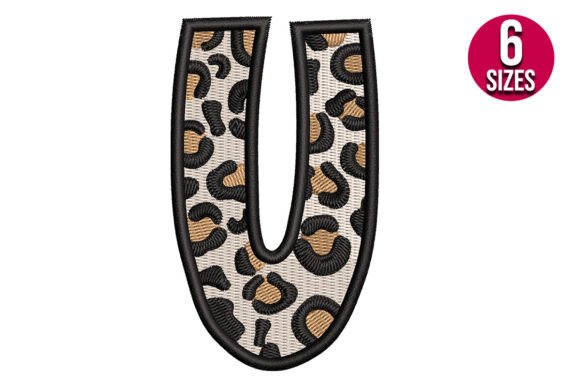
Leopard Print Alphabet Font Letter U
Urbano, ousado e felino: Review da Fonte de Letra U em Estampa Leopardo
Se você procura dar um toque selvagem e fashion a personalizações de bolsas, camisetas ou presentes, a Letra U em Estampa Leopardo chega como a escolha perfeita. Este desenho de bordado máquina combina a elegância da tipografia bold com a ousadia da estampa animal print, garantindo resultados que chamam a atenção em qualquer projeto.
- Design impactante – A letra U robusta, preenchida com o padrão de leopardo, cria contraste visual imediato, ideal para quem quer se destacar.
- Aplicações ilimitadas – Perfeita para personalizar bolsas, camisetas, bonés, almofadas, quadros decorativos e até artigos de papelaria.
- Facilidade de bordado – O design foi otimizado para costura limpa, com pontos bem distribuídos que evitam excessos de tensão e garantem durabilidade.
- Alta resolução – Cada detalhe da estampa de leopardo é reproduzido com clareza, mesmo em tamanhos menores, mantendo a nitidez da textura.
Em resumo, a fonte de letra U em estampa leopardo é a combinação ideal de estilo e praticidade. Seja para um presente exclusivo ou para ampliar a identidade visual da sua marca, este design eleva qualquer peça a um nível premium de moda streetwear.